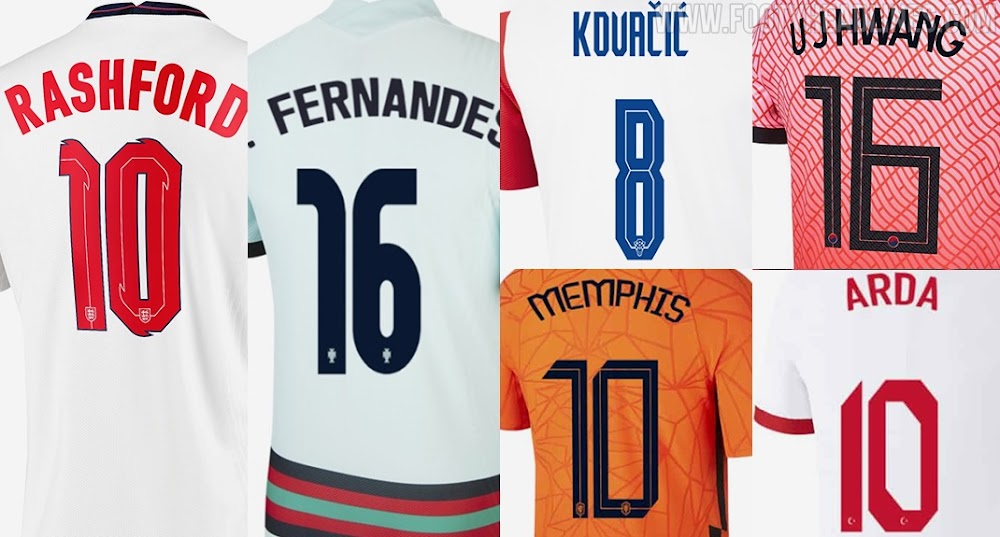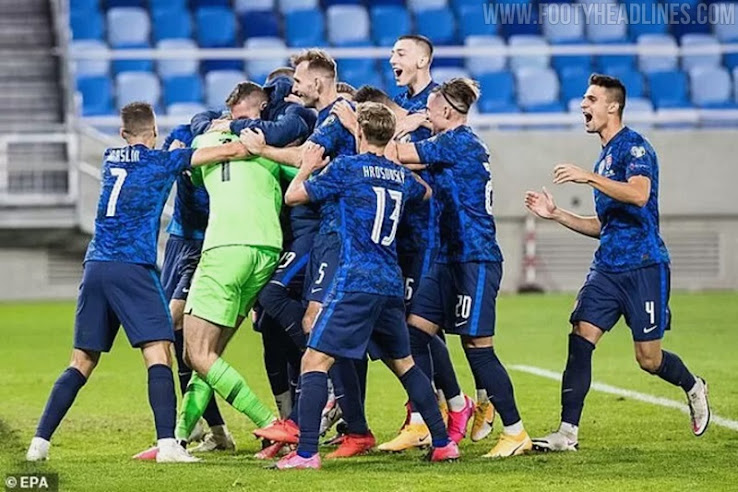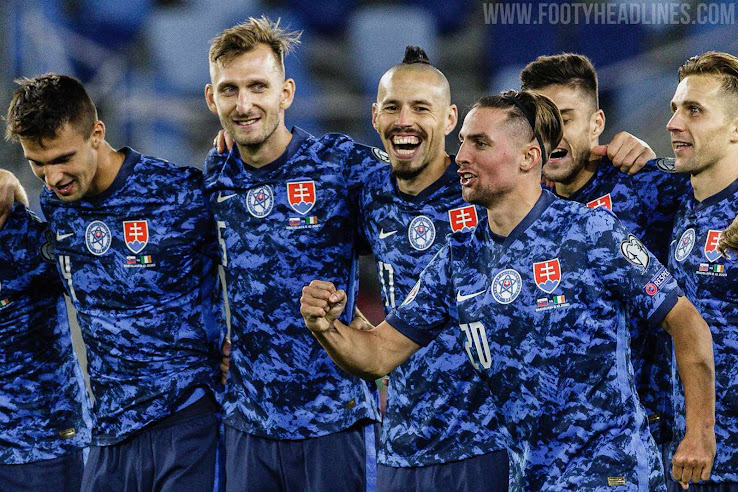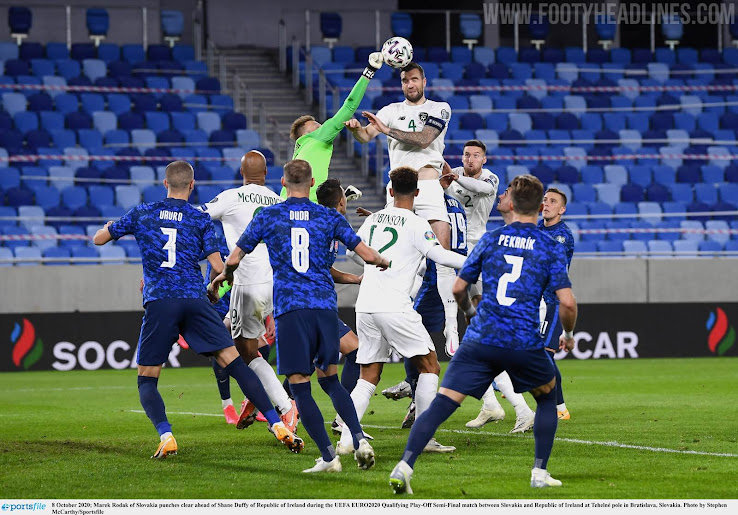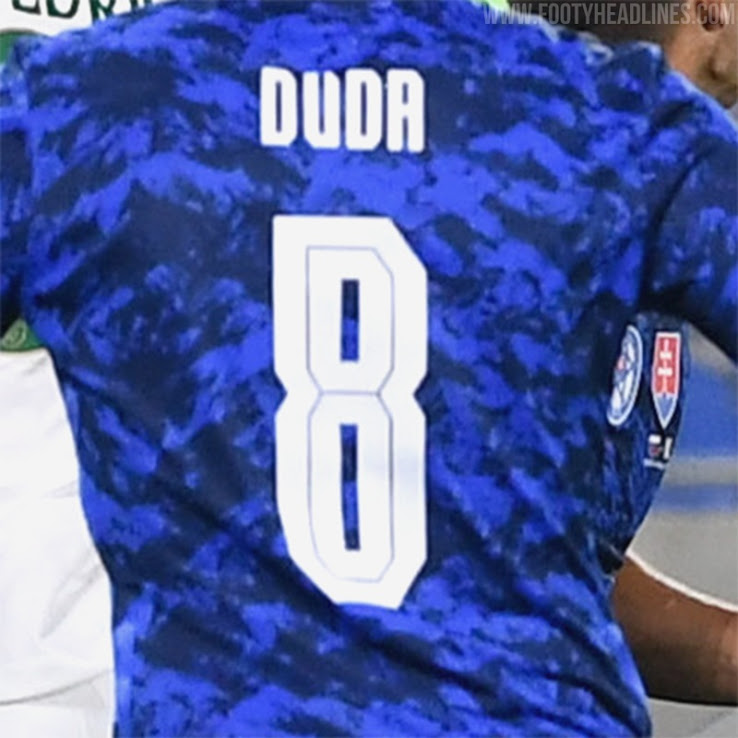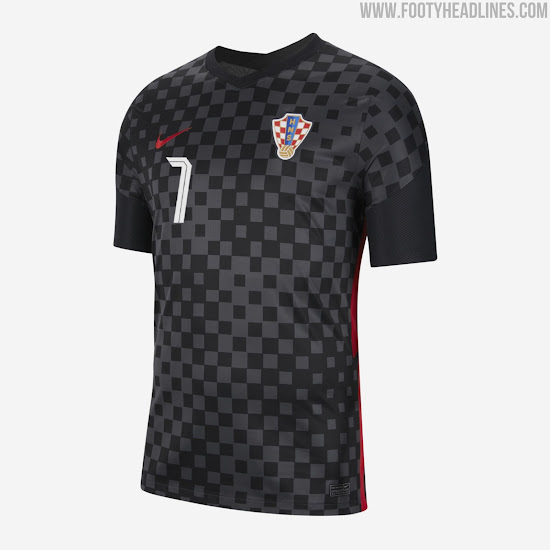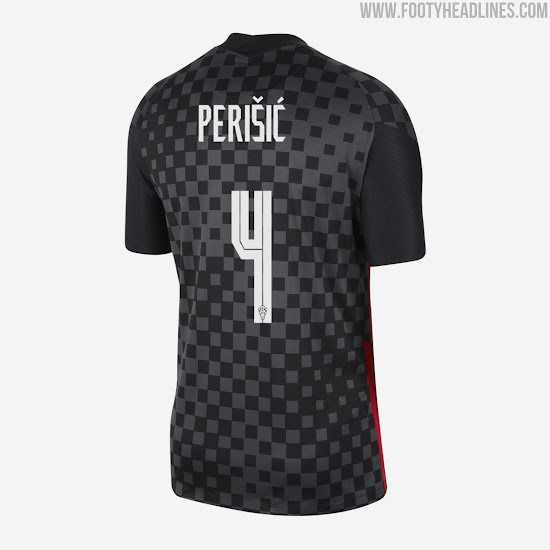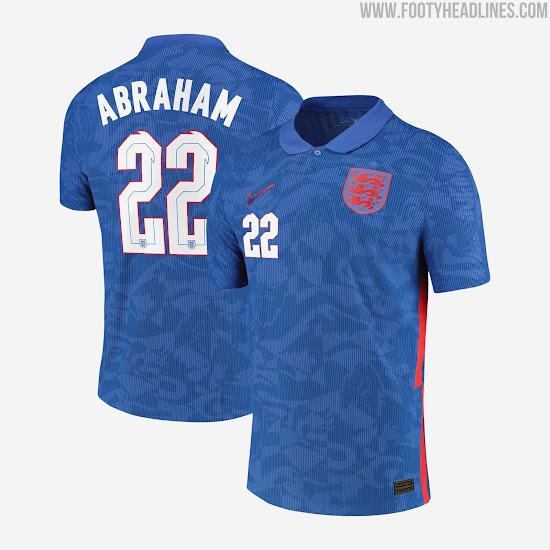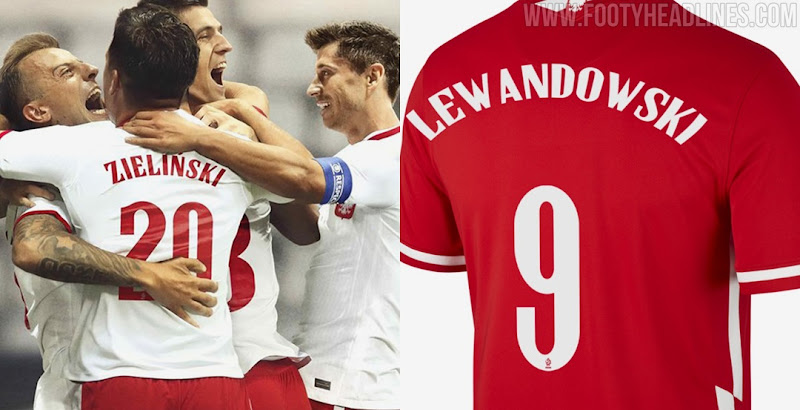
Einzigartig: Alle Nike 2020 Trikot-Schriftarten für Nationalmannschaften veröffentlicht - England, Niederlande, USA & viele mehr
Update: Die Fußball-Nationalmannschaft der Slowakei hat ebenfalls eine kundenspezifische Schriftart von Nike erhalten. Die Schriftart hat ein ähnliches Konzept wie die England 2020 Trikot-Schriftart.
Zusammen mit den 2020er-Trikots der Nationalmannschaften hat Nike einen Satz maßgeschneiderter Trikotschriften für England, Frankreich, Kroatien und die USA herausgebracht.
Nike 2020 Trikot-Schriften für Nationalmannschaften
Die neuen Nike 2020 Trikot-Schriften für Nationalmannschaften wurden im Gegensatz zu denen von Adidas und Puma exklusiv für jedes Land entworfen, um das Aussehen der Trikots zu verbessern.
Nike hat nicht für alle ihre Teams neue Schriften auf den Markt gebracht - die Niederlande haben beispielsweise keine neue Trikot-Schriftart erhalten.
Slowakei 2020 Schriftart
Kroatien EURO 2020 Schriftart
Die neue Kroatien 2020 Trikot-Schrift hat einen ähnlichen Stil wie die Kroatien WM 2018 Schrift. Sie hat einen kantigen Sanf-Serif-Stil, der zu den Karos auf den Ärmeln passt.
Nike England 2020 Trikot Schriftart
Die Schriftart für das Nike England 2020 Trikot weist ein bemerkenswertes Design auf, das die Optik des Trikots aufwertet. Laut Nike ist die exklusive Schrift "von der Identität der Three Lions inspiriert".
Frankreich 2020 Schriftart
Die neue Frankreich UEFA EURO 2020 Trikot-Schrift hat ein klassisch angehauchtes Design. Die Schriftart auf dem Frankreich 2020 Heimtrikot ist weiß / marineblau, während die Schrift auf dem Frankreich 2020 Auswärtstrikot königsblau / weiß ist.
Nike Portugal EURO 2020 Trikot Schriftart
Die Schrift des Nike Portugal EURO 2020 Trikots ist eine moderne Interpretation der Schriftart des Landes, die zwischen der Weltmeisterschaft 2006 und der EURO 2012 verwendet wurde. Die Zahlen und Buchstaben der neuen Portugal EURO 2020 Trikot-Schrift sind dicker und wirken weniger rund. Die Kanten sind nicht rund, sondern eckig.
Niederlande EURO 2020 Schriftart
Nike Polen EURO 2020 Schriftart
Exklusiv für den Polnischen Fußballverband entworfen, unterscheidet sich die Nike Polen 2020 Trikot-Schrift stark von den anderen Nike 2020 Schriftarten - der für die Polen EURO 2020 Trikots verwendete Schriftstil hat einen Serifenstil, im Gegensatz zu den anderen, die einen serifenlosen Stil haben.
Türkei EURO 2020 Schriftart
Nike USA 2020 Trikot-Schriftart
Die Schriftart für das Nike USA 2020 Trikot besticht durch einen bemerkenswerten, dennoch modernen Look, der großartig zum Trikot passt.
Nike Südkorea 2020 Trikot-Schriftart
Die Schriftart des Nike Südkorea 2020 Trikots besticht durch einen modernen und geschmeidigen Look. Die Schriftart hat viereckige Looks für die meisten Nummern, abgesehen von der Nummer 7.
Nike Südkorea 2020 Trikot-Schriftart veröffentlicht